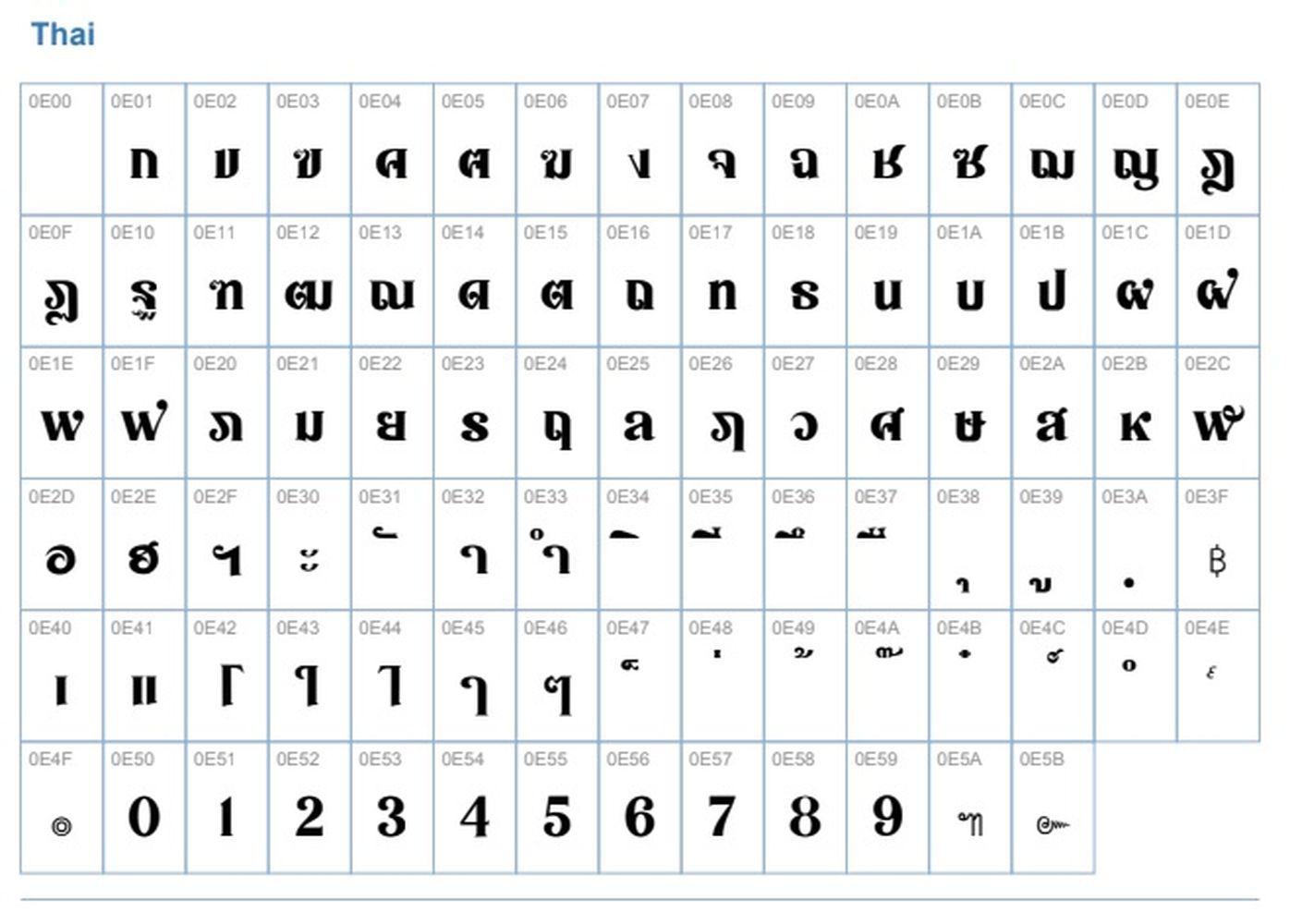
ฟอนต์ วงเพื่อน
Sarun N
ไม่ชอบคิดเอง แต่ชอบต่อยอด  :21:
ฟอนต์วงเพื่อนมีตัวอักษรแค่ เ-พ -ื -่ อ-น ที่เหลือให้เราคิดเองว่าตัวต่อไปมันน่าจะเป็นแบบไหน
คิดซิคิด....
เอ้า พอจินตนาการเพิ่มแล้วสวยกว่าต้นฉบับอีกครับ :30: แย่แล้วๆๆๆ
เสร็จแล้ว ไม่แก้แล้ว
เป็นฟอนต์ที่จองคิวไว้ว่าจะปล่อย แต่สุดท้าย ไม่ได้ปล่อย เพราะมันเป็นฟอนต์พิการ